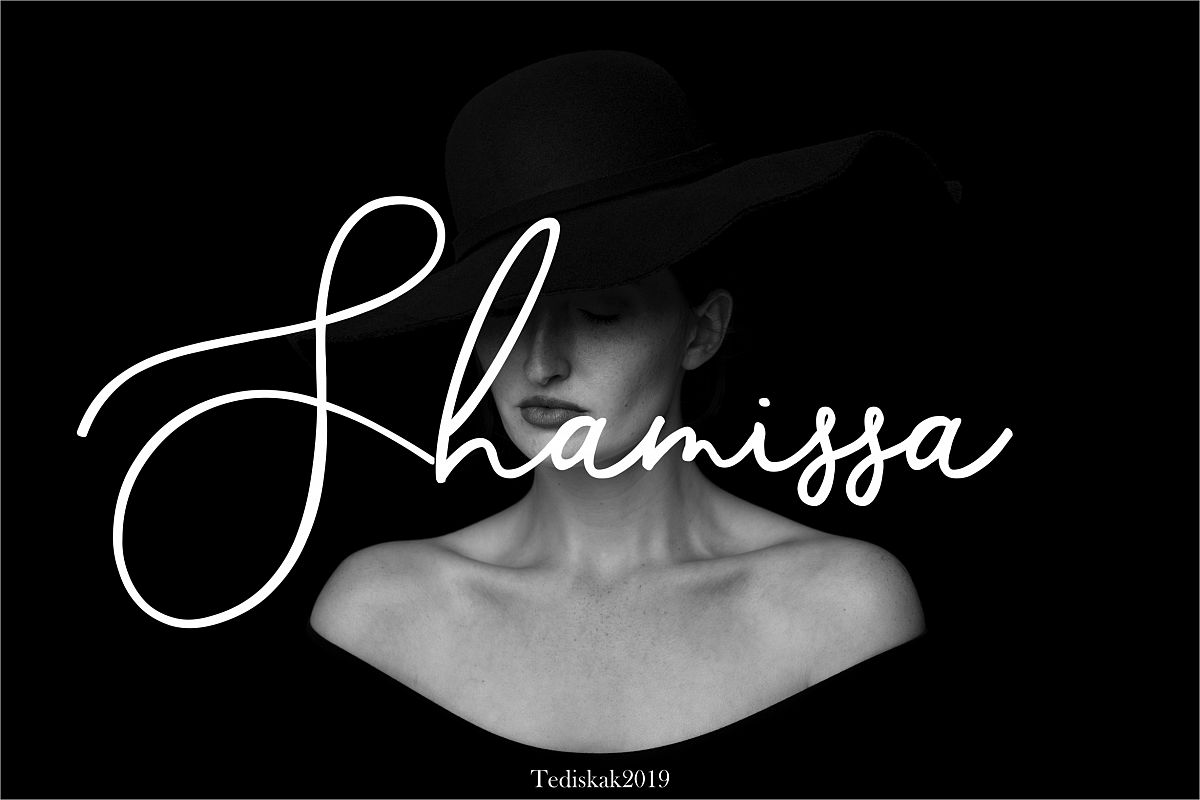
Shamissa
Shamissa sebuah karya font yang murni tulisan tangan, memiliki karakteristik tersendiri dengan gaya font Script. ini sangat cocok untuk undangan, tanda tangan, blog, media sosial, kartu nama, merek produk.
Shamissa memiliki standar Stylistic, Stylistic Alternate, Stylistic Sets. dan termasuk huruf besar dan kecil, angka dan tanda baca. Fitur font ini adalah;   * Ligatur standar
* Alternatif Gaya * Alternatif
Kontekstual